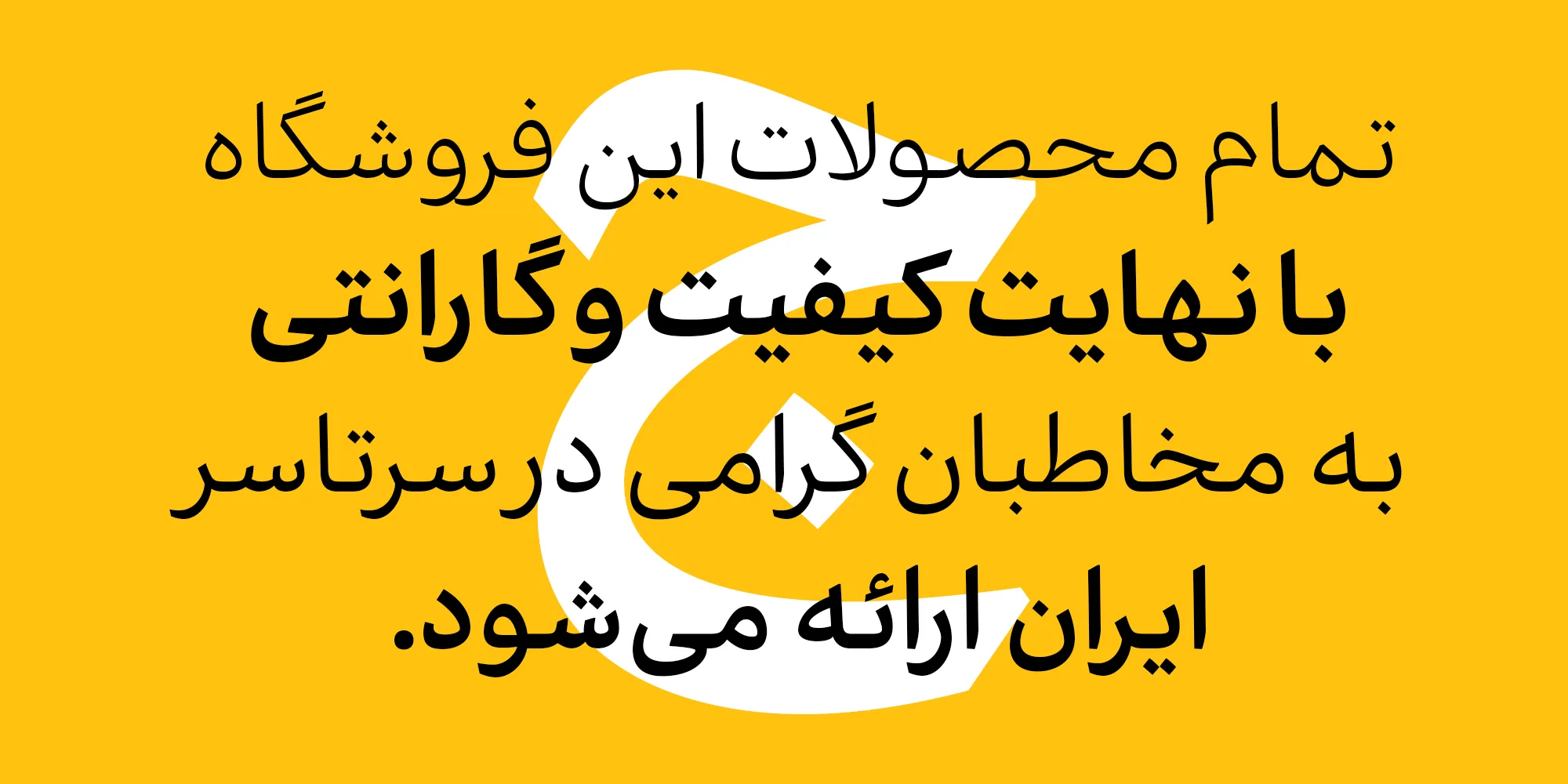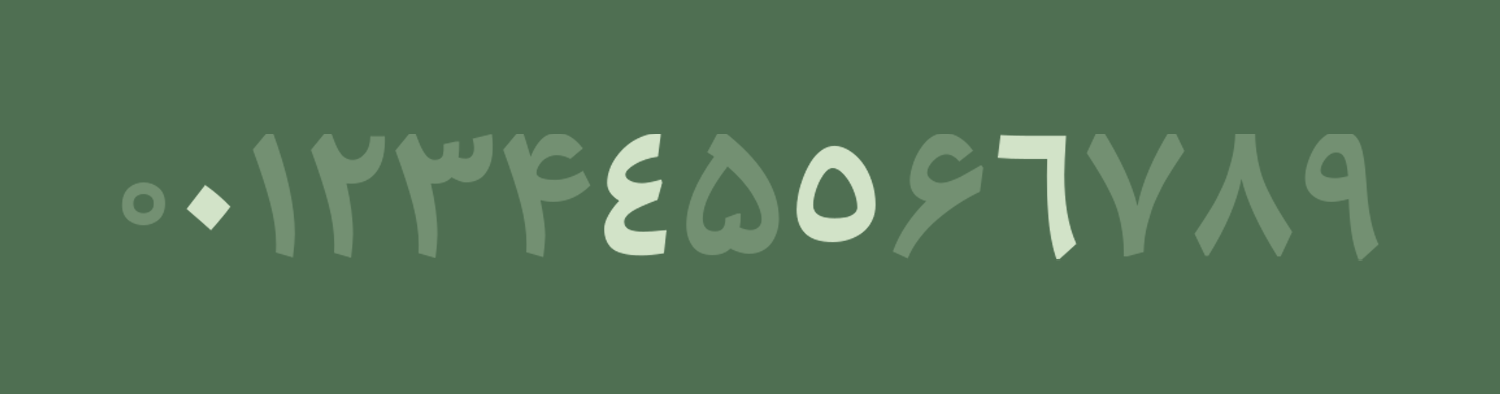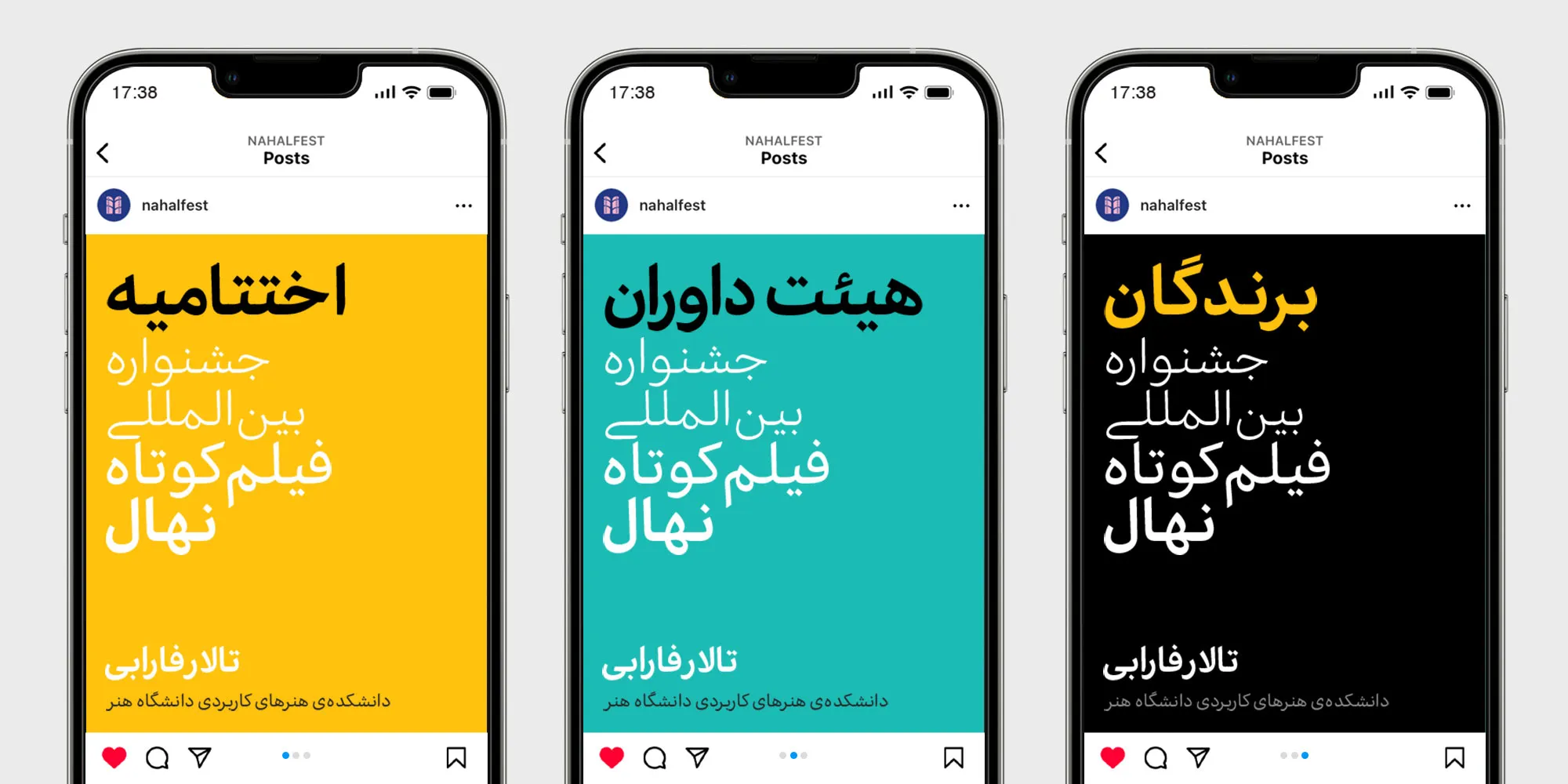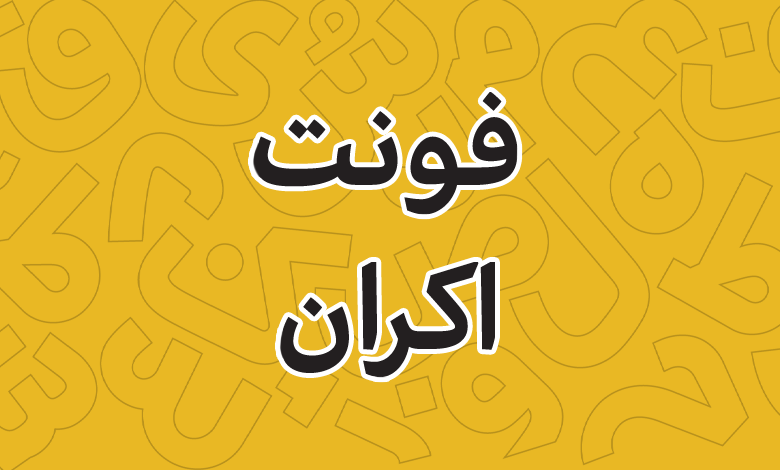
فونت اکران (Ekraan)
| نام | اکران |
| طراح | بهمن اسلامی، رضا غفاری |
فونت اکران (به انگلیسی: Ekraan) قلمی در سبک سنس و مناسب متن است که در ۵ وزن مختلف برای استفادههای متنوعی همچون طراحی رابط کاربری، استفاده در مطبوعات، فضای وب و دیجتال در نسخهای بازسازی شده از فونت تجرید طراحی شده است.
طراحان این تایپفیس رضا غفاری و بهمن اسلامی هستند که این فونت را برای استفاده در یک برنامه تلویزیونی فوتبال طراحی کردهاند که با ترکیبی از ظرافت خوشنویسی اصیل ایرانی و طراحی مدرن ایجاد شد. اما حالا این فونت برای استفاده عمومی در ۵ وزن مختلف و پشتیبانی از فرمتهای گوناگون در دسترس قرار گرفته است.
در ادامه این نوشته از سایت فونتچی به نقد و بررسی فونت اکران خواهیم پرداخت که قلمی مناسب برای طراحی رابط کاربری بوده و علاوه بر این با وجود وزنهای متعددی که در نسخههای مخصوص وب دارد، میتوانید برای فونت سایت و اپلیکیشن موبایل نیز از آن استفاده کنید.
یکی از مهمترین نکات در طراحی رابط کاربری موبایل، استفاده از صفحه نمایشی است که در نمایشگرهایی با وضوح پایین خوانایی را تا حد بسیار بالایی تامین کند.
فونت اکران مشابه با دیگر فونتهای مناسب طراحی رابط کاربری، از این نظر عملکرد عالی دارد. بنابراین چه در حال تماشای یک بازی فوتبال با یک دستگاه تلفن همراه کوچک یا یک صفحه تلویزیون بزرگ باشید، میتوانید از حس خوشنویسانهی زیبای این فونت لذت ببرید.
سبک طراحی و وزن فونت اکران
فونت اکران در قالب یک پروژه بازسازی شده از فونت تجرید در قالب تایپفیس طراحی شده است. تفاوتهای نسبتا جزئی و آشکارا با آن قلم دارد که شامل ایجاد خطور براقتر و استخوانیتر، منحنیهای ظریفتر و ساختار مدرن و بهروزتر میشود که با تلفیقی در کنار خوشنویسی سنتی ایرانی، اما به شکل مدرن امروزی طراحی شده است.
فونت اکران شامل ۵ وزن لایت، رگولار، مدیوم، سمی بولد و بولد است که همگی چه برای زبانهای خاورمیانهای و چه لاتین از این وزن به صورت مشترک پشتیبانی میکنند. برای زبان لاتین انگلیسی این فونت طراحی بهخصوصی در نظر گرفته نشده و همان گلیفهای حروف لاتین را با فونت پیشفرض در خود جایداده است. اما برای حروف فارسی و عربی، گلیفهای خاص فونت در نظر گرفته شده است.
پشتیبانی از زبان فارسی و عربی
فونت اکران از زبان فارسی به صورت پیشفرض پشتیبانی کرده و علاوه بر اینکه تمامی حروف اصلی و اعراب فارسی را در خود دارد، کاراکترهای خاص و اعداد به شکل فارسی نیز در آن جای گرفته است. از این قلم فارسی میتوانید در طراحی خود در محیطهای مختلفی استفاده کنید که شامل متنهای کوتاه تا بلند میشود.
اما به لطف رسم خط فارسی بودن زبان عربی، از این قلم میتوان در زبان عربی نیز استفاده کرد که ضمن پشتیبانی از حروف، ارعبا و گلیفهای مشترک دو زبان، پشتیبانی از اعراب و تنوینهای عربی، حروف خاص همچون «ك، ي، ة، ؤ، ئ» و اعداد عربی «٠٤٥٦» را در خود جای داده است.
با اینکه به صورت رسمی در صفحه این پروژه اعلام شده از فونت فارسی و عربی پشتیبانی میکند، اما امکان استفاده از آن را برای زبان اردو نیز دارید. با این تفاوت که محدود به حروف مشترکی خواهد بود که محدود به زبان فارسی بوده و برخی حروف خاص نظیر «ﮧ، ﮩ، ے» را نیز در خود به منظور حروف جایگزین دارد.
پشتیبانی اعداد عربی و فارسی هک شده
فونت اکران یک فونت با استدانداردهای یونیکد برای هر زبان است. این فونت برای هر دو زبان فارسی و عربی از اعداد به صورت استاندارد پشتیبانی میکند تا متناسب با هر زبانی استانداردهای درستنویسی را رعایت کنید.
اعداد عربی «٠٤٥٦» که دارای تفاوت جزئی با اعداد فارسی «۰۴۵۶» هستند در این فونت بهطور کامل پشتیبانی میشوند و متناسب با زبان صفحه کلید تایپ خواهند شد.
بر اساس همین نسخه مخصوص یک نسخه دیگر هم از فونت برای توسعه نرمافزاری برای زمانی که بخواهید از فونت انگلیسی دیگری استفاده کنید در نظر گرفته شده که فاقد حروف و اعداد انگلیسی است و تماما از حروف و گلیفهای زبان فارسی استفاده شده است.
با نصب وزنهای پنجگانه فونت اکران در سایت میتوانید از هر وزن در بخشهای متعددی مثب عناوین، تیترها، متون و تگهای خاص استفاده کنید که هر کدام شکل و شمایل خاصی را به متن شما خواهد داد و با توجه به ضخامت مختلف در وزنهایی که دارد، یک رابط کاربری و ساختار یکپارچه را در اختیارتان قرار میدهد.
جدیدترین نسخه فونت اکران ورژن ۱.۰ است که در دی ماه ۱۴۰۲ در ۵ وزن طراحی شده است. این فونت مناسب متن را میتوانید برای استفاده در طراحی رابط کاربری موبایل و انواع اپلیکیشن مورد استفاده قرار دهید که وزنهای کاملی را تشکیل داده و با توجه به جدید بودن این قلم در بحث بهبود تجربه کاربری تاثیر مثبتی روی کسب و کارتان خواهد داشت.